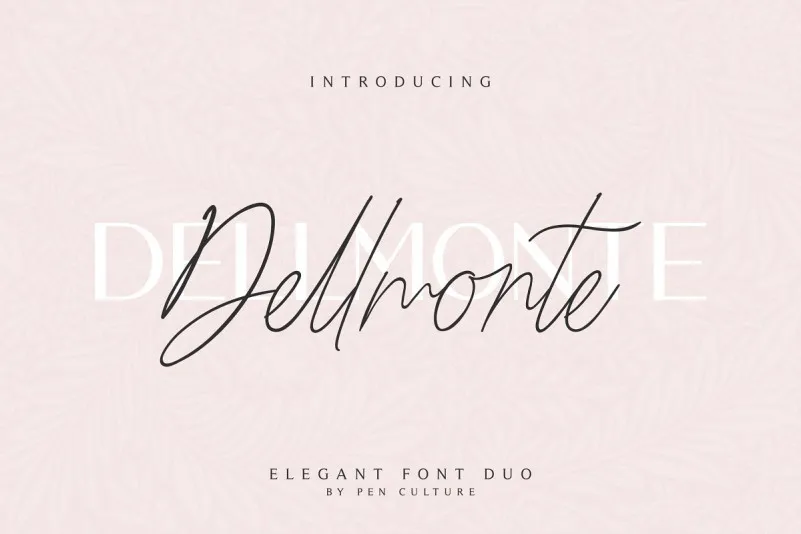
Dellmonte Sans Font – Download Grátis
Bem-vindo ao mundo do design com a Dellmonte Sans Font. Esta elegante família de tipos oferece uma experiência única para tornar seus projetos ainda mais sofisticados e modernos. Com suas curvas refinadas e bordas sedosas, a Dellmonte Sans é perfeita para aqueles que desejam dar um toque especial aos seus trabalhos gráficos. Essa fonte vem em duas variantes: sans-serif e script. As características específicas do OpenType incluem gírias (94 ligaturas), suporte multilíngue (incluindo símbolos monetários), caracteres maiúsculas completos, números padrão e muitas outras funcionalidades úteis para a criação de qualquer tipo de design. A Dellmonte Sans é ideal para designers gráficos de todos os níveis, desde branding até revistas digitais, oferecendo facilidade de uso e resultados impressionantes.